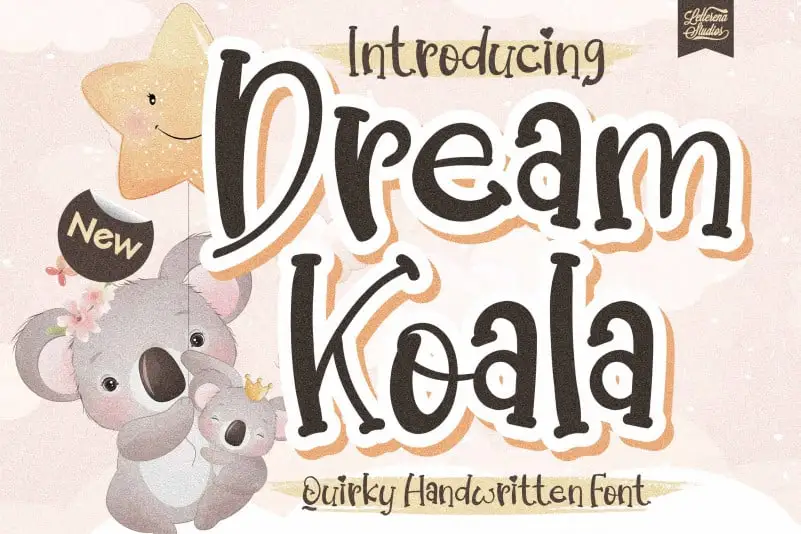
Dream Koala Display Font – Download Grátis
A Dream Koala Display Font é uma fonte que captura a essência das lembranças de infância — a caligrafia quase irônica e encantadora dos desenhos animados. Essa elegante e descontraída tipografia carrega consigo um toque único, trazendo para cada projeto criativo uma sensação fresca e amável que destaca sua personalidade de forma única. Seja em um site pessoal ou um banner publicitário, a Dream Koala Display Font está certa para transformar qualquer mensagem em algo inconfundivelmente seu. Designada pelo designer letterenastudios, esta fonte não apenas é uma escolha inteligente para quem busca uma estética divertida e eficaz, mas também traz um potencial sem igual de transformar suas ideias criativas no nível mais alto possível. Experimente a Dream Koala Display Font hoje e dê vida à sua narrativa visual.